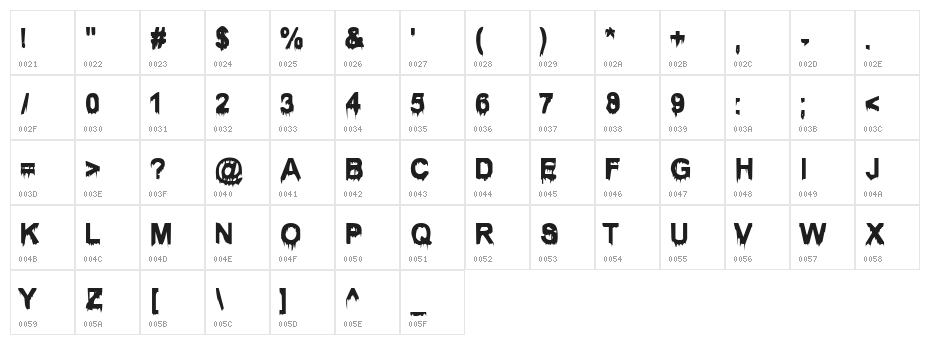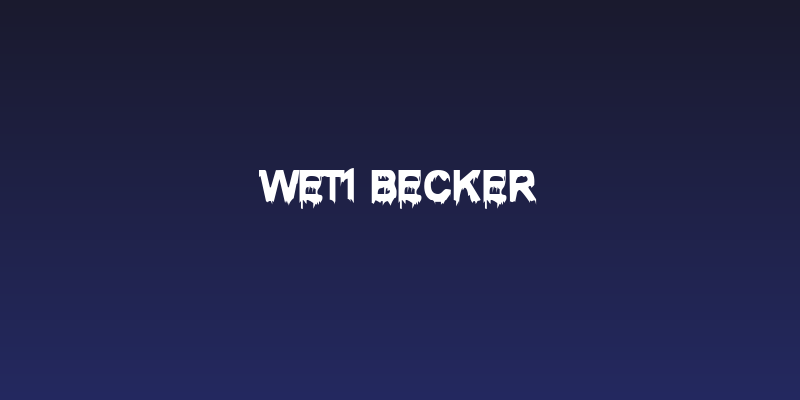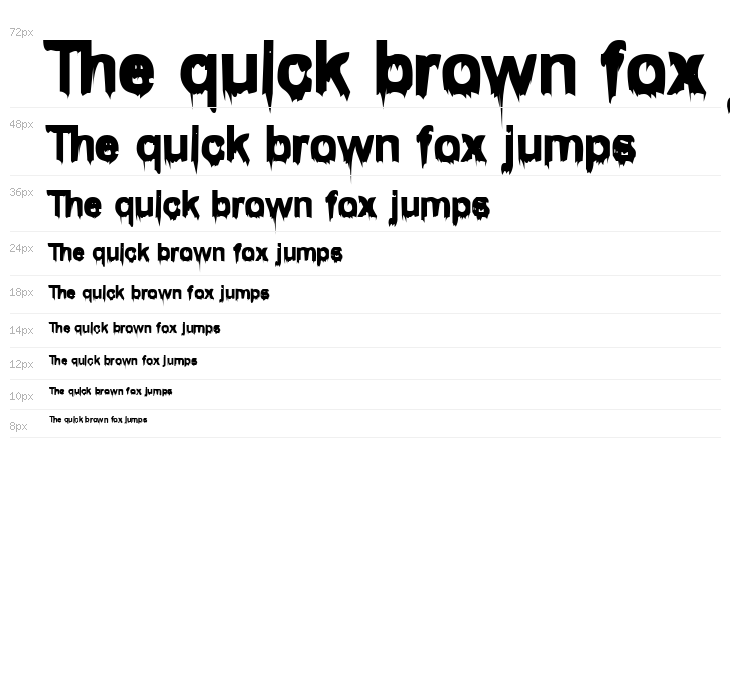
Wet1 Becker Font
| Progetti proposti | Ideal for Halloween-themed designs, horror movie posters, spooky event invitations, or any project requiring a dramatic, eerie aesthetic. |